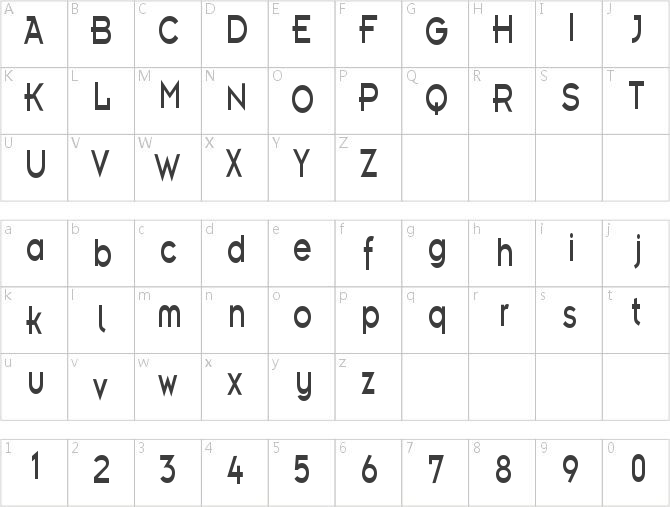
emblemcondensedregular 详情页
emblemcondensedregular
emblemcondensedregular介绍
emblemcondensedregular字体字库是一款让人赏心悦目、百看不厌的英文字体,适合各类广告和产品包装设计应用,字体大小0.04MB,格式为ttf字体,上传用户是文生电脑,作者/版权方为未知